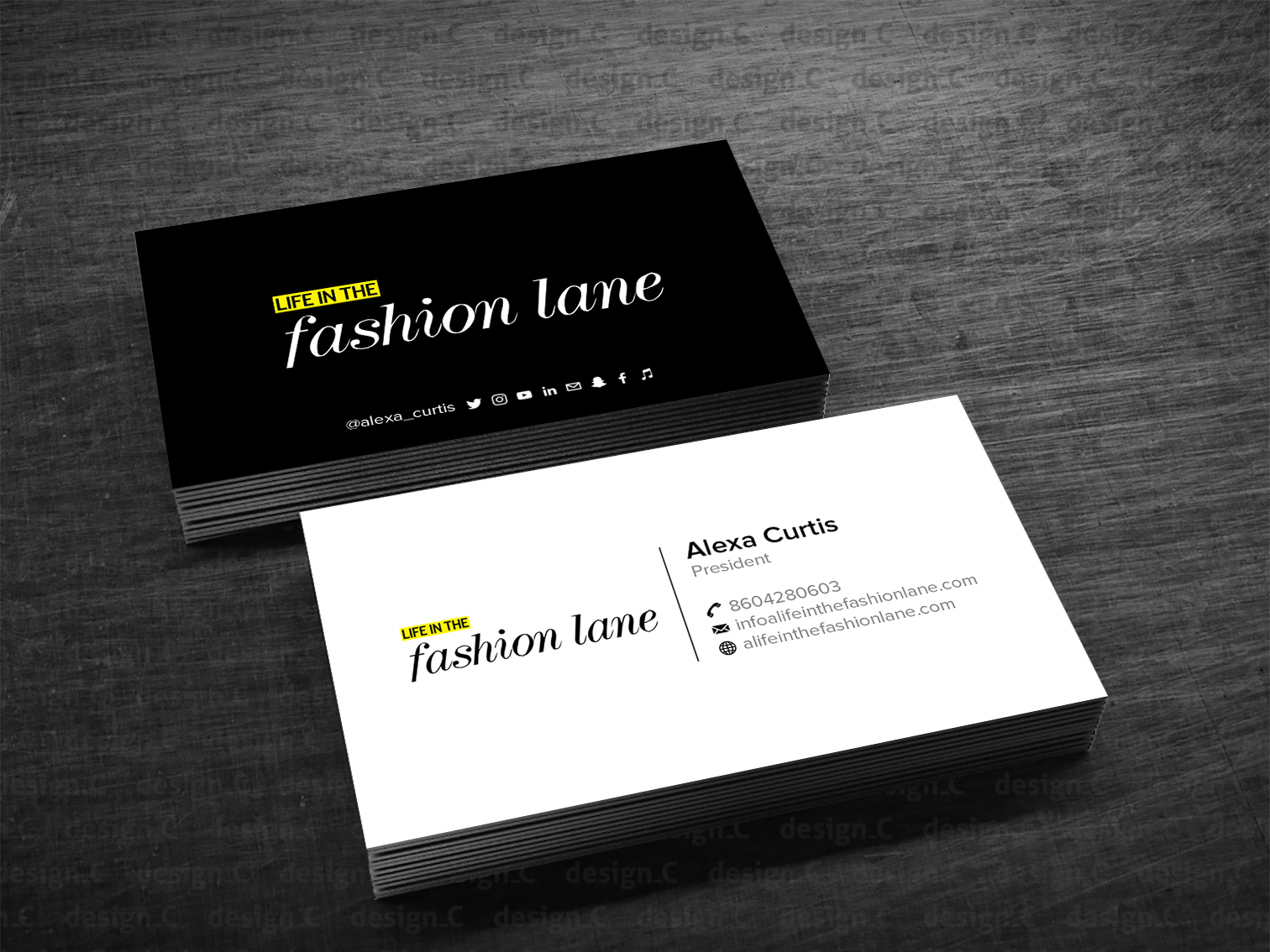
О том, как важны в современном мире деловом мире визитки, вы наверняка хорошо знаете. Визитки не только несут информацию о вашем имени и фамилии, должности и месте работы. Визитки демонстрируют уровень вашего вкуса и понятие о деловом этикете. Поэтому наша компания Print Market с удовольствием берет на себя задачу создать каждому клиенту уникальные визитные карточки, изготовление которых мы гарантируем всегда в срок и с отличным качеством.
Одним из клиентов была ведущая инвестиционная банковская компания Джаспэн Кэпитал Партнэрс (Jaspen Сapital Рartners), которая работает на рынках Западной и Восточной Европы, в том числе и в Украине. Компания отлично зарекомендовала себя как профессионала и новатора в своем деле, компетентного и надежного партнера. Визитки для них мы сделали строгими и элегантными, выдержанными в корпоративных двух оттенках синего цвета.
Для чудесного Капиталист Паба «Дон Олио» мы сделали визитки настоящего итальянского мафиози – черно-белые. Рекомендуем посетить это милое заведение – там не только вкусно кормят блюдами итальянской кухни, но и поят отличным качественным пивом и крепким черным кофе. А также развлекают книгами, настольными играми и компьютерными играми на приставках.
Для компании «СОТА» мы сделали визитки с достаточным количеством информации и всеми необходимыми контактами. Эта компания занимается продажей мобильных телефонов, цифровой и портативной техники, комплектующими и аксессуарами к ней.
Специалисты сети магазинов «СОТА» могут все – от установки и настройки программного обеспечения до профессиональных консультаций и подбора оптимальных тарифов различных операторов.
Также мы сделали деловые визитки для сотрудников акционерной страховой компании «ИНГО Украина», которая уже более 20 лет трудится на рынке Украины. Компания крупная, работает в 25 городах по всей территории страны. В офисах компании трудятся более 600 сотрудников.
Визитки мы сделали в полном соответствии с пожеланиями заказчика – строгий красивый шрифт, корпоративные цвета и четкий логотип компании.
Еще мы создали личные визитные карточки замечательному врачу-стоматологу. Красивым шрифтом и интересной композицией визиток мы хотели подчеркнуть, что врач – женщина, очаровательная и привлекательная.
Каждая визитка – это не просто бумажка с фамилией и адресом, это продуманная композиция, шрифт и цвет. Визитка – ваш рекламный щит, ваш молчаливый агент. Поэтому мы индивидуально подходим к каждому нашему клиенту и стараемся «на отлично» решить те задачи, которые он перед нами ставит.
Есть много бесплатных шрифтов по всему Интернету, но может быть довольно сложно найти тот, который выделяет естественную атмосферу. В этой витрине мы собрали 20 бесплатных рукописных шрифтов для любых ваших потребностей, будь то приглашение на свадьбу, превью-изображения для блога, дизайн креативных визиток.
Шрифты, которые мы собрали здесь, могут быть смешаны с любым дизайном, чтобы соответствовать теме дизайна или придать ему остроту. От утонченной элегантности до чистой грубости — это одни из лучших рукописных и рукописных шрифтов, которые вы можете найти там.
пекарня
Пекарня от StereoType представляет собой полный набор альтернативных глифов плюс 13 лигатур и штрихов, доступных для личного использования.
Она всегда гуляет одна
Описанная как необычный шрифт кисти, она всегда работает в одиночку от Runes & Fonts и доступна для коммерческого использования. Свяжитесь с автором для получения лицензии
Variane Script Font
Variane Script Fontby Boy Moch Tomi — это простой и чистый курсивный шрифт, который хорошо работает как для светлых, так и для темных настроек
Сценарий береговой линии
Свободный плавный курсивный шрифт Shorelines Script от The Branded Quotes не выровнен по фиксированной высоте или интервалу, выделяя очень естественный рукописный вид
Reis
Reisby Marcelo Reis Melo идеально подходит для постеров и заголовков, благодаря своей громкой природе.[[Скачать]
Гумно
Stackyard от Mans Greback — сильный, организованный шрифт с последовательным уклоном
A HandMade Шрифт
HandMade Fontby Gaston Jacquier — округлый, чистый шрифт с красивыми легкими штрихами
Чеддер джек
Cheddar Jack от Brittney Murphy Design — это очень естественный взгляд на рукописные шрифты.
Это хорошо работает с дизайном упаковки вольным стилем
Кицунэ Удон
Kitsune Udon от Rory Harnden — это обширная коллекция из более чем 1194 динамических рукописных символов, с 4-16 символами для каждого символа
BeWicked
BeWicked от Джеффа Бенша вдохновлен титульной картой ситкома Bewitched TV
Эйфория
Euphoria от Typesenses — это неформальный, игривый шрифт на уровне поздравительной открытки
Лось шрифт
Шрифт Moose от Jake Luedecke Motion & Graphic Design — это коллекция из 94 символов, которая выглядит как очаровательная попытка имитировать шрифт старой пишущей машинки.
Vtks Love U
Vtks Love U от VTKS DESIGN — это необработанный и преднамеренно неполированный шрифт, который помогает выделять эту тревожную атмосферу
MRF Веснушчатый лимонад
Легкий штрих и причудливый, этот MRF Веснушчатый Лимонад от MonkeyRoodles Fonts будет хорошо смотреться на пригласительных билетах
Milasian
Красивый и элегантный шрифт Milasian от Mans Greback доступен в трех вариантах: тонкий, средний и жирный.
Впустую
Wasted от StereoType поставляется с 14 различными штрихами и двумя стилями подчеркивания. Коммерческая лицензия доступна
Scriptina Font Family
Scriptina Font Family от Apostrophic Labs имеет громкие волны, которые будут одинаково хорошо смотреться на модных свадебных приглашениях, как на татуировках
Popsies Font
Для этого действительно правдоподобного рукописного шрифта этот грубый шрифт Popsies от StimulEye Fonts создает впечатление
Milasian Circa
Milasian Circa от Mans Grebasck — более распространенная и более округлая версия Milasian (также показанная в этом списке)
Программы для Windows, мобильные приложения, игры — ВСЁ БЕСПЛАТНО, в нашем закрытом телеграмм канале — Подписывайтесь:)
Какой размер шрифта для визитной карточки? Избегайте маленьких и слабых – Блоги Silkcards
- Inspire
При разработке визитной карточки вам необходимо убедиться, что ваш бренд передает правильное сообщение, а текст читаем и ясен.
Это может быть проблемой, поскольку визитная карточка такая маленькая, так как же узнать, какой размер шрифта выбрать для визитной карточки?
Размер шрифта визитной карточки: вы используете слишком мелкий шрифт?
Одной из самых больших ошибок является выбор маленького шрифта просто для того, чтобы вы могли втиснуть тонну информации в этот прямоугольник размером 3,5 x 2 дюйма.
Связано: Стандартные размеры визитных карточек, которые следует использовать
Учитывая размер визитной карточки, при выборе размера шрифта следует помнить о двух вещах:
- Два маленьких размера затруднят чтение , однако визитную карточку обычно рассматривают вблизи.
- Слишком большой размер занимает ценное место на визитной карточке.
Размер шрифта 10-11 пт идеально подходит для основного текста, а 7-8 пт можно использовать для контактной информации. Однако это ни в коем случае не правило.
Это действительно зависит от вашего дизайна
Для выделения можно использовать более крупные и жирные шрифты, а размер действительно зависит от макета и дизайна карты.
Связано: Креативные способы использования оборотной стороны визитной карточки не выглядит хорошо, когда он маленький. Связано: В чем разница между гарнитурой и шрифтом? Предполагая, что в руководстве по стилю вашего бренда нет спецификаций, определяющих, какой шрифт использовать, вот несколько общих правил шрифтов, которые хорошо работают и обеспечивают удобочитаемость на некоторых из лучших визитных карточек: Шрифты с засечками или шрифты с небольшими декоративными полосами на концах каждого символа, как правило, немного сложнее читать, чем шрифты с засечками или без них. Полезный пример — Times New Roman : Этот шрифт очень легко читается, но это один из наиболее распространенных шрифтов. Чтобы сделать его более уникальным, используйте вариации и параметры стиля, такие как выделение курсивом. Один из вариантов — также использовать его для более простых областей карты, таких как контактная информация. Если начертание шрифта достаточно толстое, шрифты без засечек читаются легче всего из всех типов шрифтов, поскольку они не содержат ненужных завитушек. Прямые, четкие линии означают отсутствие беспорядка, и вы можете использовать их в меньших размерах, чем другие шрифты, без больших потерь. Полезный пример — Myriad Pro: Этот шрифт идеально подходит для профессиональных визитных карточек. Аккуратные прописные буквы, а также закругленные хвосты делают его стильным и формальным. Письма чрезвычайно трудно читать, как и некоторые специальные шрифты. Лучший способ действий — использовать их экономно, ровно столько, чтобы правильно передать ваш бренд, и сделать их как можно больше для удобочитаемости. Полезный пример — Karat: Если ваш бренд более неформальный, вы можете использовать этот шрифт. Изогнутые буквы делают его более игривым, чем шрифты, предназначенные для официальной аудитории. Связано: Когда допустимо использовать рукописный шрифт в дизайне? Если дизайн вашей визитной карточки вызывает у вас грусть, наша команда дизайнеров может позаботиться об этом за вас. Вы не только выиграете от того, что прибьете правильные размеры, но и конечный продукт также будет отражать ваш бренд и впечатлит любого, кому вы передадите свою визитку. Не верите нам? Запросите БЕСПЛАТНЫЙ образец пакета. Содержание Лучшие шрифты для визитных карточек, вдохновляющие на творчество Выбор правильного шрифта для визитных карточек
Шрифты с засечками
Тем не менее, они передают более формальный штрих, похожий на пишущую машинку. Эти шрифты должны быть немного больше, чем обычные шрифты без засечек. Шрифты без засечек
Письма или специальные шрифты
13 лучших шрифтов для визитных карточек, которые должен попробовать каждый
Заключение Лучшие шрифты для визитных карточек, вдохновляющие на творчество
Визитные карточки считаются важным элементом брендинга.
Они используются для определения важной информации о вашей компании, чтобы люди могли легко связаться с вами в любое время. Это основная причина, почему их дизайн и презентация имеют большое значение для компаний. Они всегда стараются использовать лучшие шрифты для визитных карточек, чтобы они выглядели более привлекательными.
Как графический дизайнер, вы можете получить много заказов от клиентов на дизайн визитных карточек. Потому что каждая компания обращает на это внимание. Они знают, что эти визитки необходимы для поддержания профессионального представительства бизнеса на рынке. Он предоставляет клиентам начальную информацию о вашей компании, включая контактный телефон, адрес и другие.
Некоторые компании нанимают дизайнеров-фрилансеров для создания уникальных визитных карточек, а некоторые обращаются за помощью к брендинговым агентствам. Наем любого специализированного брендингового агентства дает им большую ценность с точки зрения опыта и знаний. Они довольно хорошо разбираются в разработке различных типов визитных карточек, точно в соответствии с требованиями клиентов.
В этой статье мы рассмотрим некоторые из лучших шрифтов для визитных карточек, доступных на рынке. Используя их, вы можете привнести в свои карточки фактор творчества, позволяющий людям проявлять больший интерес к вашему бизнесу.
Давайте сначала разберемся, почему выбор правильного шрифта для визитной карточки очень важен.
Logopoppin
Logopoppin — агентство графического дизайна, специализирующееся на разработке логотипов, веб-разработке, производстве видео и передовых услугах по брендингу. Мы любим внедрять инновации в бизнес с помощью технологий нового века, позволяя им улучшать свою визуальную репутацию.
Поделиться этой статьей
Поделиться на фейсбуке
Поделиться в твиттере
Поделиться на linkedin
Подпишитесь на еженедельные обновления
1. Почему шрифты имеют значение для визитных карточек?
Будучи дизайнером, вы должны знать об элементах, которые необходимы в дизайне.
Это включает в себя различные типы вещей, включая шрифты, цветовые темы и многое другое. Сочетание их всех дает идеальную форму дизайна, точно соответствующую заданным требованиям.
Говоря конкретно о шрифтах, они считаются очень важными для визитных карточек. Они всегда тщательно выбираются после изучения основной темы дизайна. Часто компании используют только мужские шрифты в качестве основного элемента дизайна визитных карточек. Вы могли видеть различные подобные примеры, доступные на рынке. В этих карточках особое внимание уделяется использованию жирного шрифта, чтобы основная информация о компании могла быть правильно выделена.
2. Лучшие шрифты для визитных карточек
Выбор лучших шрифтов для визитных карточек может быть немного сложным, особенно если вы ничего об этом не знаете. Часто люди выбирают неправильные шрифты для визитных карточек, из-за чего вся их презентация выглядит странно.
Если вы тоже один из тех парней, которые всегда путаются в выборе, вот список, составленный в соответствии с вашими требованиями.
Он включает в себя одни из лучших шрифтов для визитных карточек, оцененные ведущими мировыми экспертами в области графического дизайна.
Рассмотрим их подробнее ниже.
Хотите сделать свой бизнес
глобальным?
Наши дизайнеры помогут вам легко создать
международный бренд.
3. Лучшие шрифты без засечек для визитных карточек
Многие люди предпочитают шрифты без засечек для визитных карточек. Они выглядят действительно профессионально и аккуратно, позволяя вам старательно отображать деловую информацию на карточках.
Вот некоторые из лучших шрифтов без засечек для визитных карточек, о которых должен знать каждый дизайнер.
3.1 Helvetica
Helvetica всегда оставалась очевидным выбором многих графических дизайнеров для визитных карточек. Они предлагают классический, но смелый вид типографики, позволяя клиентам проявлять интерес к карточке. Первоначально он был создан в Швейцарии в 1957 году и с тех пор остается популярным выбором писателей и дизайнеров во всем мире.
Helvetica — один из тех винтажных шрифтов, которые определяют общий дизайн. Его простота позволяет словам правильно распространять свои мысли. Это также зависит от дизайнера, как он использует это в дизайне. Выбор размера и цвета имеет большое значение в этом отношении. Это всегда следует делать с учетом общего дизайна визитной карточки.
3.2 Futura
Если вы ищете бесплатный шрифт без засечек, который хорошо выглядит по стилю, обратите внимание на шрифт Futura. Он в основном доступен в кириллице, демонстрируя настоящий класс аккуратного стиля. Глядя на происхождение, это шрифт без засечек, вдохновленный геометрическими фигурами, особенно круглой формой.
История Futura, как и Times New Roman, очень длинная. Он был изобретен в 1927 году как общий шрифт для написания книг. С тех пор он регулярно рос, расширяя свой стиль на большее количество категорий и весов.
Сегодня Futura входит в число лучших рекомендуемых для визитных карточек. Он выглядит просто и стильно, позволяя предприятиям достойно записывать важную информацию на карточках.
3.3 Arial
Arial также очень популярен для визитных карточек из-за его жирного вида. С момента своего появления в 1982 году Arial остается основным выбором людей для написания документов, а также для дизайна визитных карточек. Он был создан Робином Николасом и Патрисией Сондерс для типографики Monotype.
Многие люди связывают Arial с Helvetica из-за похожего внешнего вида. Оба этих шрифта относятся к категории без засечек, поэтому иногда они выглядят одинаково по стилю. Однако корпус шрифта Arial намного толще по сравнению со шрифтом Helvetica. Именно это делает его более сильным и запоминающимся по сравнению с другими шрифтами без засечек.
3.4 Campton
Campton также является очень популярным шрифтом без засечек, созданным с потрясающей смелостью. Он предлагает уникальную современную атмосферу, позволяя вашим визитным карточкам демонстрировать сильную индивидуальность. Как правило, люди предпочитают использовать черный цвет, так как в нем он выглядит солиднее.
Тем не менее, вы также можете выбрать для него другие цвета, которые хорошо подходят в соответствии с требованиями вашего бренда.
4. Лучшие рукописные шрифты для визитных карточек
Помимо шрифтов без засечек, многие дизайнеры также любят использовать рукописные шрифты для визитных карточек. Они более стильные и уникальные по сравнению с категорией без засечек.
Вот некоторые из лучших шрифтов для визитных карточек, которые вы можете найти на рынке.
4.1 Kensington
Kensington — очень креативный шрифт, имитирующий форму подписи. Он выглядит очень модно из-за великолепного курсивного начертания. Как правило, они используются с комбинацией творческих цветов, таких как золотой, синий и другие. Используя их, вы можете привнести в свои карты изюминку уникальности в соответствии с последними стандартами.
Вам как дизайнеру этот шрифт покажется очень интересным. Его можно использовать при разработке визитных карточек, а также других материалов для брендинга, таких как листовки, брошюры и многое другое.
Просто убедитесь, что выбрали правильный размер, так как иногда большие шрифты выглядят очень странно в дизайне.
4.2 Bontella
Это рукописный шрифт, который предлагает классическую атмосферу курсивной категории шрифтов. В отличие от других рукописных шрифтов, его стиль немного уникален и выглядит более громоздким. Это делает его идеальным для всех типов материалов для брендинга, включая позеры, визитные карточки и другие.
Еще одно преимущество этого рукописного шрифта заключается в том, что он абсолютно бесплатный. Вы можете использовать его, просто загрузив образец файла из Интернета. Просто убедитесь, что вы выбрали правильный источник для загрузки, так как иногда поддельные веб-сайты предлагают неправильную категорию bontella.
4.3 Broadway
Broadway — это особый рукописный шрифт, который предпочтительнее использовать для фотографий визитных карточек. Стиль этой карты также демонстрирует, почему она используется для фотографий.
Это выглядит действительно художественно, демонстрируя идеальный поток элегантности в типографике.
Помимо визитных карточек, эти шрифты также можно использовать на веб-сайтах с фотографиями и на плакатах. От вас зависит, как использовать эти шрифты разных цветов и насыщенности на других материалах для брендинга. Вы можете внимательно изучить примеры, приведенные в Интернете, чтобы узнать больше о его использовании в соответствии с требованиями дизайна.
5. Лучшие шрифты с засечками для визитных карточек
Шрифты с засечками также широко используются в различных типах визитных карточек. Они выглядят довольно модно, но при этом обеспечивают аккуратный вид письменного материала.
Вот некоторые из лучших шрифтов с засечками для визитных карточек, которые вы должны попробовать сегодня.
5.1 Times New Roman
Times New Roman также стал лучшим выбором дизайнеров для создания визитных карточек. Это очень профессионально выглядящий шрифт, который придает визитным карточкам достойный вид.
История этого шрифта очень длинная, так как он был создан еще в 1931 году.
С тех пор Times New Roman остается лучшим выбором людей для написания различных материалов. Сегодня он регулярно используется в визитных карточках из-за великолепного внешнего вида. Помимо них, вы также можете использовать его в других материалах для брендинга, таких как конверты, фирменные бланки и многое другое, чтобы сделать типографику компактной.
5.2 Reptile
Название этого шрифта довольно уникально по сравнению с любым другим доступным шрифтом. Он выглядит обычным, но очень смелым на вид. Именно по этой причине он рекомендуется для визитных карточек, а также других материалов, демонстрирующих фирменный стиль.
Он доступен как в нижнем, так и в верхнем регистре, предоставляя пользователям широкие возможности для удобного использования в любом месте. Более того, он абсолютно бесплатный и его можно быстро использовать, просто загрузив образец файла шрифта из Интернета.
5.3 Butler
Butler — очень универсальный шрифт, который позволяет вам с совершенством создавать великолепные визитные карточки и другие элементы брендинга. Он вдохновлен общим стилем шрифта Bodoni, который в основном используется для логотипов. Он поставляется с различными вариациями, что позволяет дизайнерам использовать его в самых разных местах. Вы можете использовать его как в нижнем, так и в верхнем регистре. Шрифт выглядит действительно великолепно с различными типами вариаций, если его правильно использовать с правильной практикой.
6. Лучшие шрифты Google для визитных карточек
Многим людям нравятся шрифты Google из-за их бесплатного лицензирования. Вы можете легко использовать их в своих проектах, не тратя ни копейки. Вот несколько лучших шрифтов Google для визитных карточек, которые вам определенно понравится регулярно использовать.
6.1 Space Mono
Space mono — очень известный шрифт Google, разработанный Colophon Foundry.
Его стиль предлагает уникальную атмосферу 1960-х годов, смешанную с искусством современности. Он поставляется как в верхнем, так и в нижнем регистре, что позволяет вам использовать типографику на визитных карточках с вашими собственными требованиями.
6.2 Cormorant
Cormorant — это популярный шрифт Google, который среди других выглядит очень гладким и простым. Они обеспечивают элегантный вид типографики, так что ваши визитные карточки могут имитировать солидный вид. Просто убедитесь, что вы выбрали правильный цвет при использовании их в визитных карточках. Цветовая гамма шрифтов всегда играет важную роль в брендинговых материалах, особенно визитных карточках.
6.3 Work Sans
Work Sans выглядит как обычный шрифт, созданный для простоты письма. Вы можете использовать их в визитных карточках с правильным цветовым оттенком и размером в зависимости от общего дизайна. Он выглядит солидно и компактно, придавая вашей фирменной канцелярской типографике выдающийся вид.
Часто задаваемые вопросы
1. Почему важно использовать лучшие шрифты для визитных карточек?
Дизайн визитных карточек всегда оставался важной задачей для владельцев компаний. Для этого требуются креативные шрифты, которые помогут вам грамотно представить информацию о компании. Вот почему всегда рекомендуется выбирать лучшие шрифты для визитных карточек, которые могут улучшить их представление.
2. Какие шрифты без засечек лучше всего используются дизайнерами для визитных карточек?
Существуют различные типы шрифтов без засечек, используемые дизайнерами для визитных карточек. Однако наиболее распространенными среди них являются Helvetica, Futura, Arial и другие.
3. Назовите некоторые популярные шрифты для визитных карточек, используемые дизайнерами?
На рынке можно найти несколько типов рукописных шрифтов, используемых для визитных карточек. Самые популярные среди них – Kensington, Bontella, Broadway и другие.
4. Почему для визитных карточек выбран шрифт Times New Roman?
Times New Roman — стандартный и очень популярный шрифт, используемый для написания различных документов. Он также используется в различных типах или материалах для брендинга, таких как визитные карточки, листовки и многое другое. Выглядит достойно и просто, поэтому дизайнеры предпочитают его при создании визиток.
5. Где я могу найти лучшие шрифты для визитных карточек?
В Интернете доступно множество ресурсов, где можно найти креативные шрифты для визитных карточек. Некоторые из лучших сайтов, которые предлагают бесплатные шрифты для визитных карточек, включают Fonts.com, DaFont, FontSpace и другие.
Заключение
На этом мы завершаем весь наш блог, в котором мы перечислили некоторые из лучших шрифтов для визитных карточек, доступных на рынке. Все мы прекрасно знаем, насколько важны визитки для любой компании. Они не только демонстрируют вашу контактную информацию, но и определяют тему вашего бренда.
Поэтому рекомендуется тщательно оформлять свои визитные карточки, используя правильные шрифты.